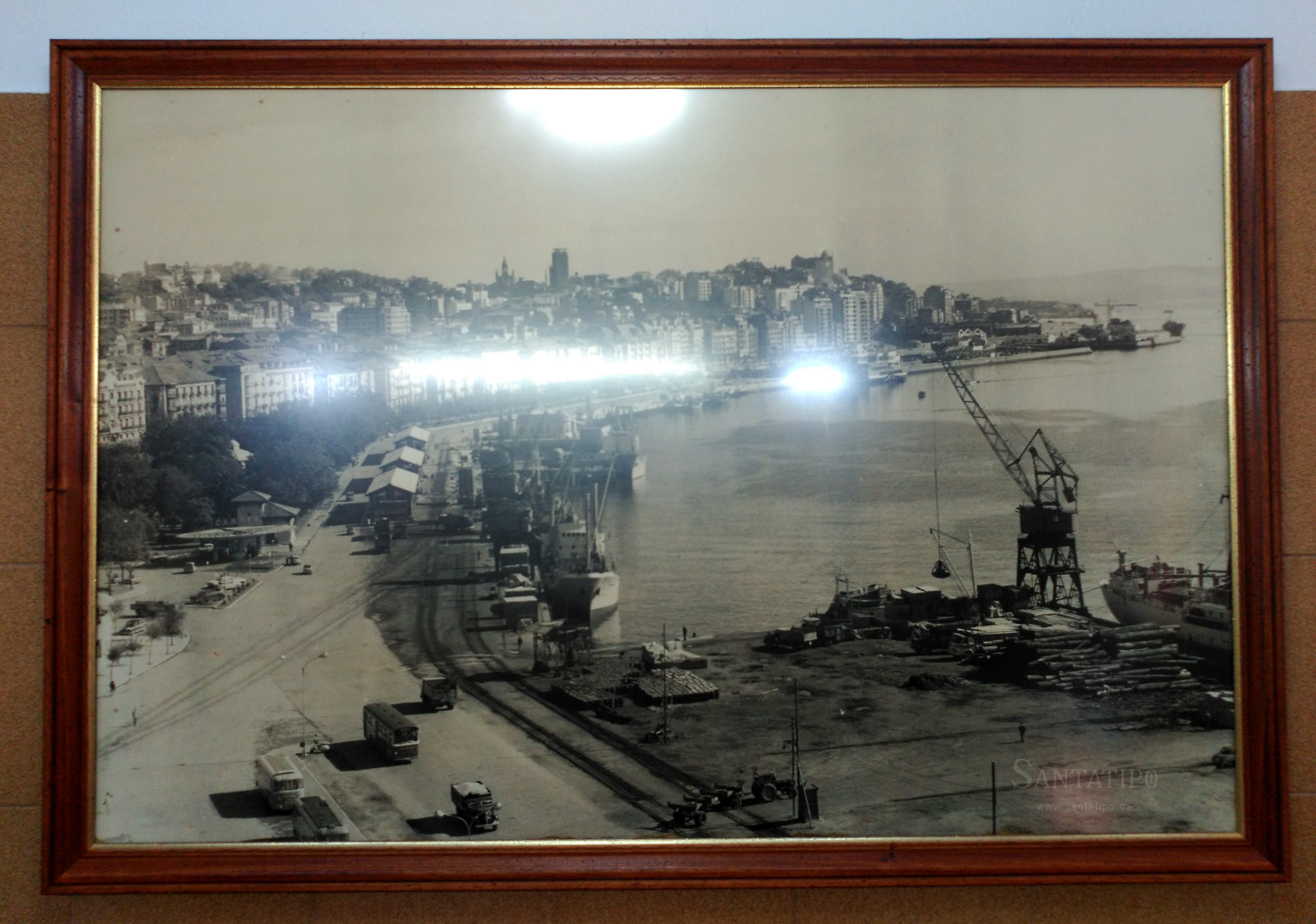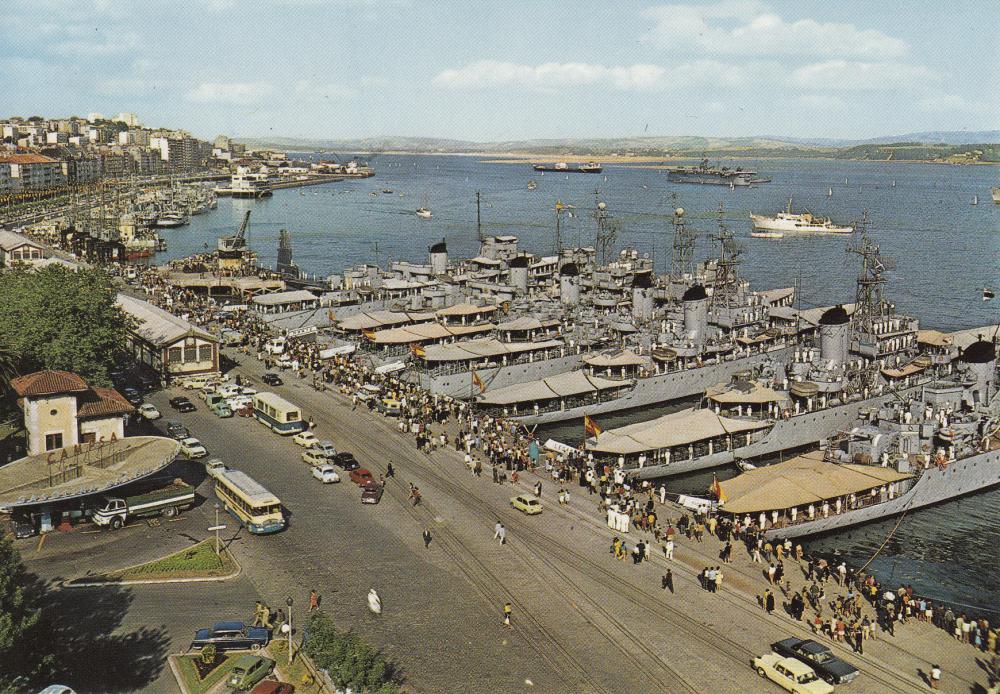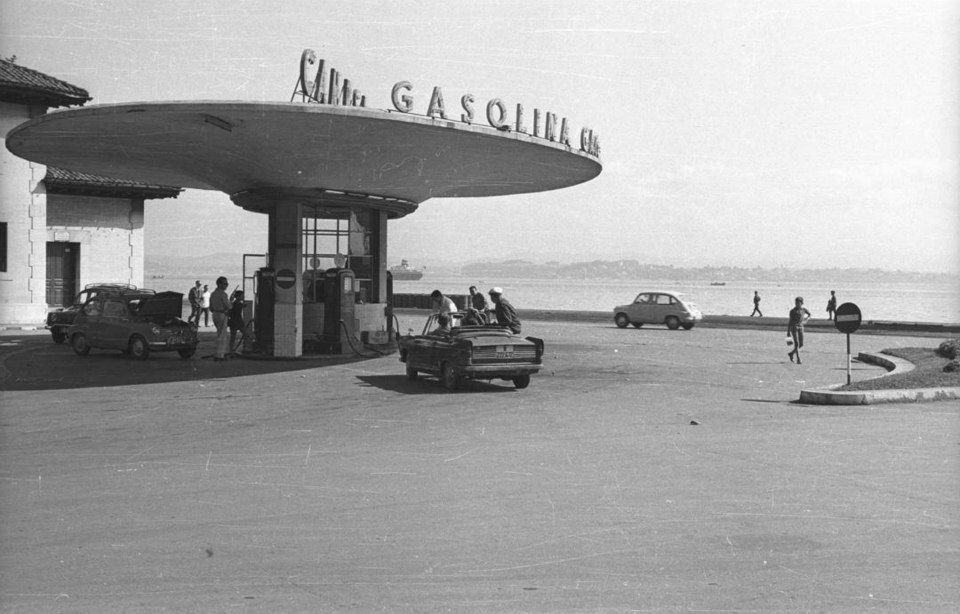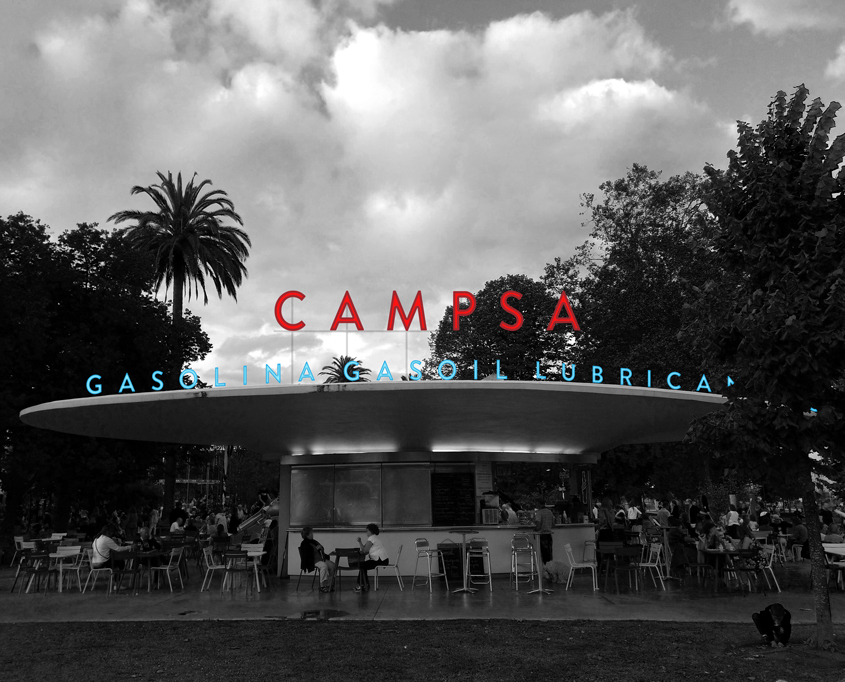
Gasolinera CAMPSA – Jardines de Pereda
En los Jardines de Pereda aún se conserva un elemento arquitectónico único, se trata de lo que fue una Gasolinera encargada por CAMPSA en 1952 y que permaneció activa hasta 2014. Hoy tras la remodelación de los Jardines y la construcción del Centro Botín, se ha convertido en un cafetería. En este completo artículo de Pecios de la Arquitectura Montañesa tenéis todos los detalles de la obra.
En relación al rótulo, era muy característico y moderno, con una tipografía grande, limpia y en colores Rojo y Azul, acorde al diseño de la obra. También destacaba su iluminación en neón. Muchas fotos en las que se ve la gasolinera en activo, se ve ilegible o parcialmente el rótulo, por lo que era difícil sacar la linea inferior. Por suerte, y gracias a un café en un pequeño bar de Santander hay una foto de formato grande, hasta ahora desconocida, en la que se ve esa zona del puerto y se puede leer el rótulo. El rótulo fue desmontado tras el cambio de concesión de la gasolinera.
Foto de colección desconocida vista en el «Bar Stewart». En ella se puede leer el rótulo. (Foto de Santatipo).
Aquí se puede ver la tipografía, así como el neón montado sobre las letras. (1964, Fondo Pablo Hojas. CDIS / Fuente: Pecios de la Arquitectura Montañesa)
Aquí podemos ver los colores del rótulo (fuente: Pecios de la Arquitectura Montañesa)